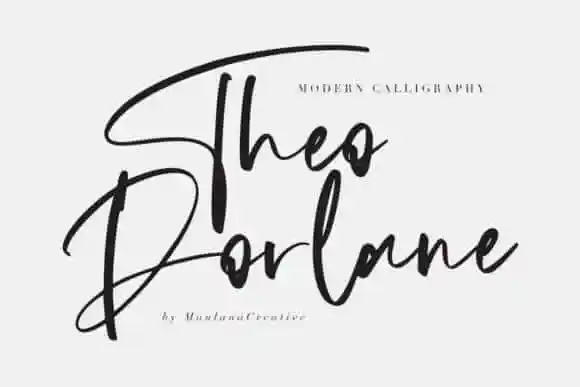
Theodorlane Calligraphy Font – Download Grátis
A Theodorlane Calligraphy Font é uma opção irresistível para os designers que procuram dar vida a design visualmente elegante e sofisticado. Ideal para marcações, desde as identidades corporativas até cartões de aniversário e propagandas, esta fonte proporciona um ar luxuoso e casual em suas obras. Com sua estética minimalista, esta coleção é perfeita para quem procura uma mistura de elegância com personalidade na criação de design. Ela foi criada por Maulana Creative, uma empresa experiente no ramo da fontes e digitais. Este não é apenas um conjunto de letras para a sua próxima peça de propaganda, mas uma ferramenta poderosa que transformará seu trabalho em algo único e imediatamente reconhecível. O design da Theodorlane Calligraphy Font certamente fará do seu próximo projeto um verdadeiro stand out.